Как словолитни поддерживают шрифты после выпуска
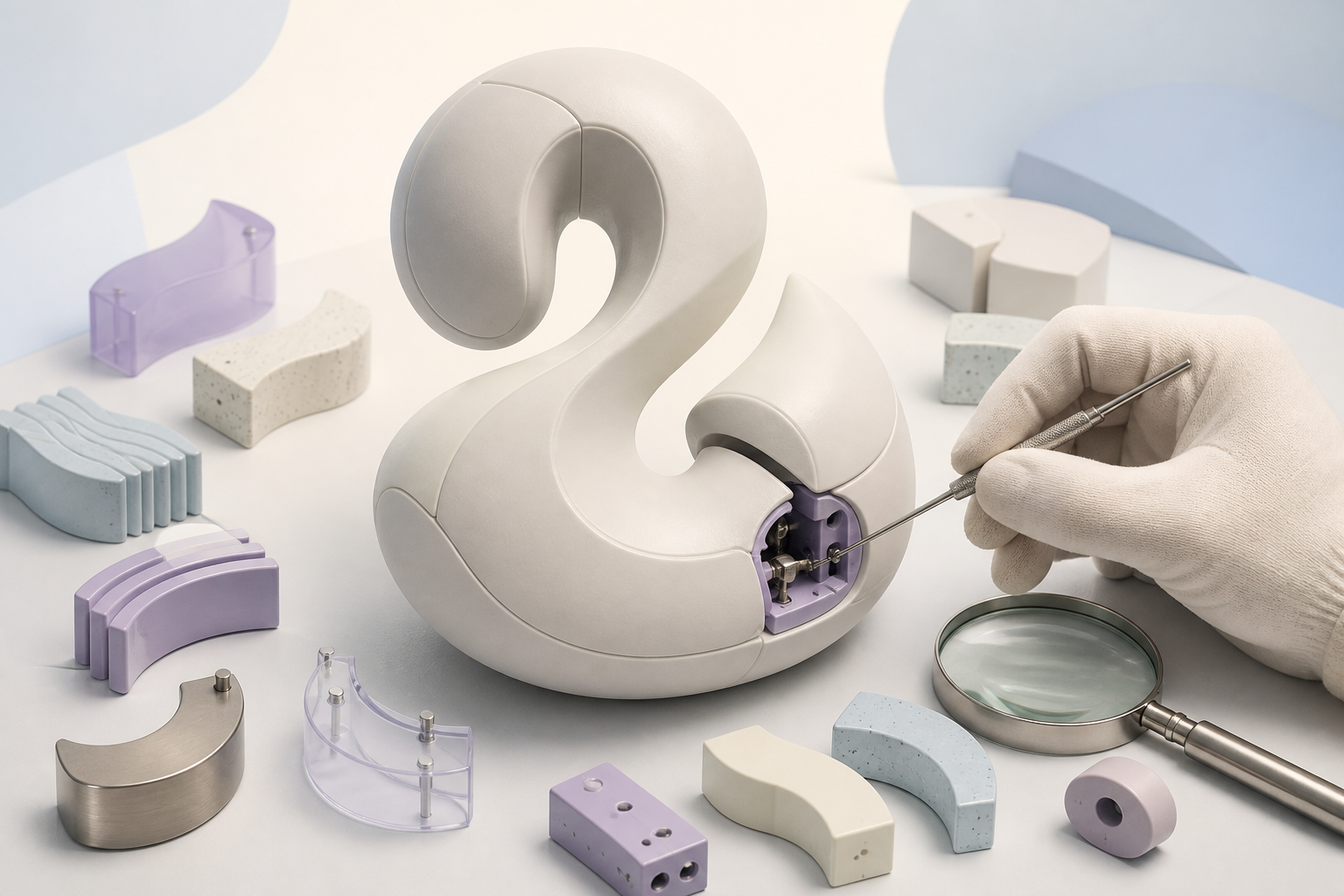
Словолитни поддерживают шрифты после выпуска через регулярные обновления, техническую проверку, расширение языковых наборов, исправление ошибок в OpenType-функциях и консультации пользователей. Хорошая гарнитура продолжает развиваться после релиза: авторы реагируют на найденные проблемы, уточняют документацию и сохраняют совместимость с рабочими сценариями дизайнеров, издателей и разработчиков.
Почему выпуск шрифта не завершает его разработку
Шрифт выходит в мир не как статичная картинка, а как программный продукт для набора текста. Его используют в разных операционных системах, редакторах, браузерах, приложениях и языковых средах. В процессе такого использования обнаруживаются сценарии, которые невозможно полностью воспроизвести в студии: редкие сочетания знаков, необычные размеры, сложные направления письма или конфликт отдельных OpenType-функций.
Кроме того, после релиза меняются задачи самого проекта. Заказчику может понадобиться кириллица, которой не было в первой версии, набор математических символов, дополнительные начертания или веб-формат. Поэтому поддержка шрифта включает не только исправление дефектов, но и управляемое развитие семейства без потери уже работающих макетов.
Какие задачи решают словолитни после релиза
Работа словолитни после выпуска обычно складывается из нескольких направлений. Одни задачи заметны сразу, например исправление пропавшего символа. Другие проявляются постепенно: улучшение кернинга, уточнение названий функций или подготовка файлов для новых платформ. Вместе они поддерживают качество набора и уменьшают риск того, что шрифт станет непригодным для современной среды.
- Исправляют ошибки в контурах, метриках, кодировках и таблицах шрифта.
- Уточняют кернинг, трекинг, вертикальные метрики и поведение знаков в строке.
- Добавляют языки, диакритические знаки, валютные символы и специальные глифы.
- Обновляют OpenType-функции: лигатуры, альтернативы, малые капители и числовые наборы.
- Выпускают новые форматы, например отдельные версии для веба или переменных шрифтов.
- Поддерживают документацию, лицензирование, changelog и ответы на вопросы пользователей.
Технические исправления: от глифа до таблиц OpenType
Самый очевидный вид поддержки — исправление ошибок в рисунке знаков. У глифа может оказаться незамкнутый контур, лишняя точка, неверное направление кривой или неправильное выравнивание относительно базовой линии. На крупном кегле такая ошибка заметна визуально, а в маленьком размере проявляется как пятно, разрыв или неравномерная плотность строки.
Не менее важны внутренние данные файла. Таблицы OpenType управляют кодировкой, метриками, подстановками и позиционированием знаков. Если в них есть ошибка, буква может отображаться, но неправильно участвовать в лигатуре, не соединяться с диакритикой или занимать неожиданную ширину. Словолитня проверяет такие случаи в редакторах шрифтов, браузерах и макетах с реальными текстами.
Практический пример: дизайнер верстает заголовок с французскими кавычками, длинным тире и сочетанием букв «ТА». В ранней версии гарнитуры кавычки могут иметь неверные боковые поля, а пара «ТА» — слишком плотный кернинг. Обновление исправляет метрики и пару кернинга, после чего тот же макет выглядит аккуратно без ручного раздвигания символов.
Расширение языков и наборов символов
Языковая поддержка — отдельный этап работы, а не механическое добавление недостающих букв. Для каждого языка нужно учесть диакритические знаки, правила сочетания, регистр, формы кавычек, тире, числовые символы и особенности набора. В кириллице важно сохранить единый характер букв, а не просто дорисовать их по аналогии с латиницей.
После расширения словолитня должна проверить не только отдельные глифы, но и пары, слова и многоязычные строки. Например, добавление польских или чешских диакритик влияет на высоту знаков и может изменить визуальный ритм абзаца. Если шрифт используется в интерфейсе, проверяют также сортировку, отображение дат, валют и пользовательских имён.
OpenType-функции и совместимость с рабочими программами
Современная гарнитура часто содержит функции OpenType: стандартные и исторические лигатуры, стилистические альтернативы, дроби, порядковые обозначения, пропорциональные и табличные цифры, верхние индексы и малые капители. После выпуска авторы проверяют, включаются ли эти функции корректно и одинаково ли трактуются в популярных графических и текстовых редакторах.
Совместимость не означает абсолютное одинаковое поведение везде. Программа может поддерживать только часть функций, браузер — по-разному отображать переменные оси, а приложение — использовать собственный механизм рендеринга. Поэтому словолитня описывает ограничения и выпускает исправления там, где проблема относится к самому файлу, а не к особенностям конкретной платформы.
Новые начертания, оси и версии семейства
Поддержка может расширять семейство: появляются новые веса, курсив, конденсированные варианты, капители или переменная версия. Важно, чтобы новые начертания сохраняли общую систему пропорций и не ломали визуальную иерархию. Пользователь ожидает, что заголовок, подпись и основной текст будут выглядеть частью одного семейства, даже если используются разные файлы или значения оси.